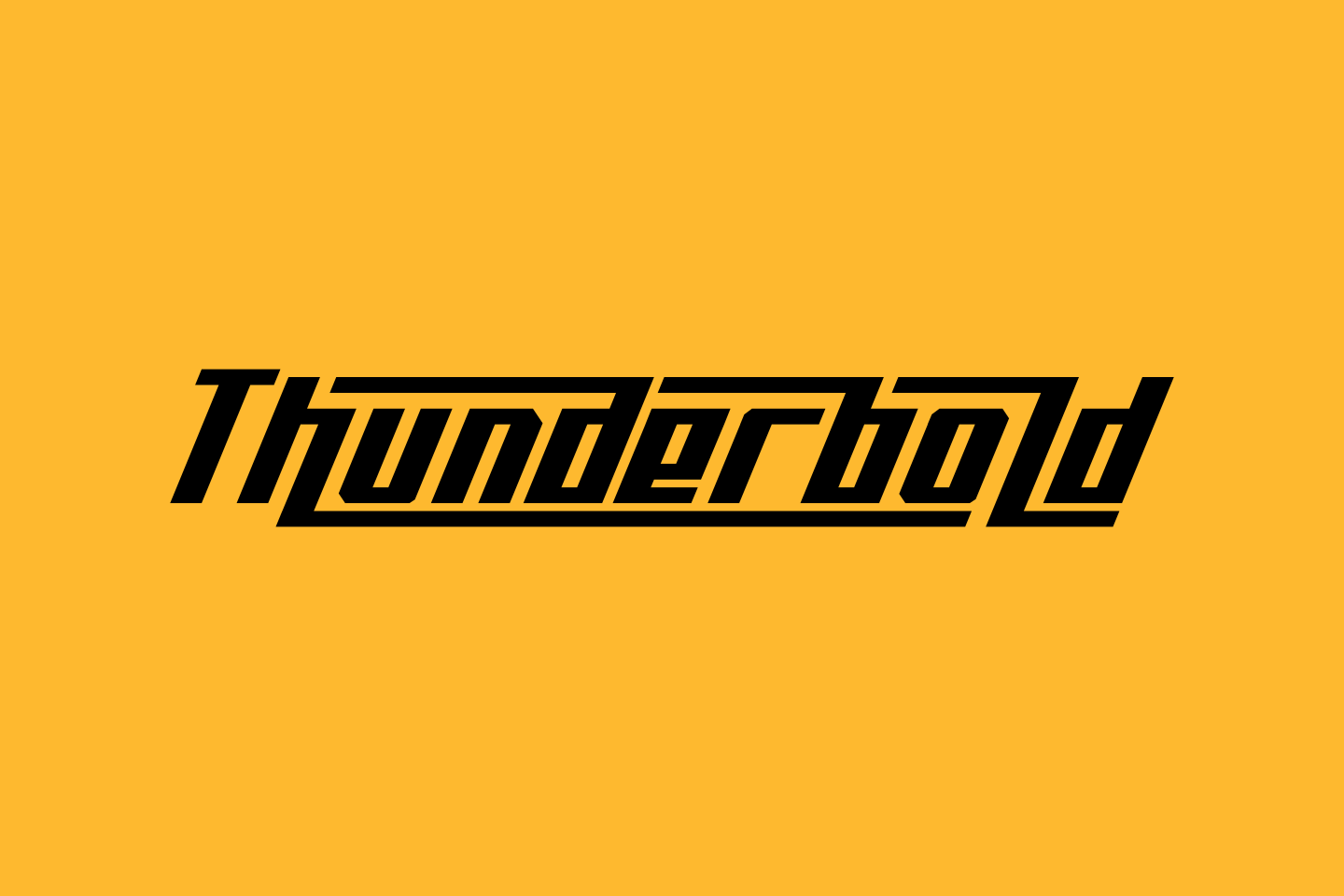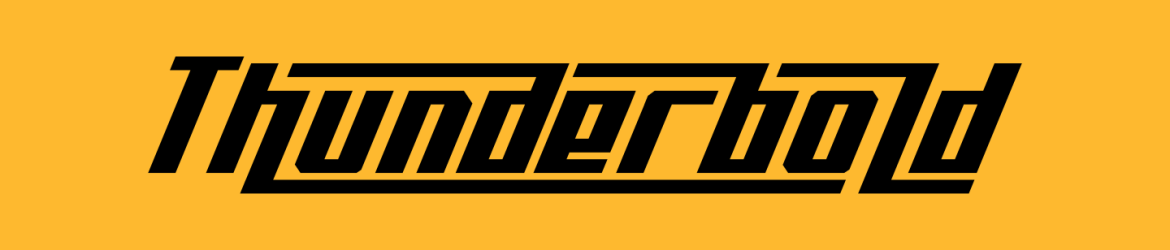
Thunderbold Typeface – Download Grátis
A Thunderbold Typeface é uma escolha perfeita para os projetos que exigem destaque e força visual. Com seu design robusto, esta fonte foi criada especialmente para a mídia outdoor: desde outdoors gigantes até as mais pequenas notificações de corrida. Seu formato bold torna-a ideal para qualquer aplicação onde você deseja chamar atenção à primeira vista. O destaque se deve em grande parte ao seu recurso alternativo, que permite uma variedade infinita de aplicações e criação de novas identidades visuais sem necessariamente ter de recorrer a fontes adicionais. Seu design poderoso faz-a perfeitamente adequada para logotipos e marcas de negócios, bem como banners, outdoors, selos de corrida ou quaisquer outros casos que exigem um apelo impactante. Composta para destaque em grandes escala, a Thunderbold é uma escolha segura se você está procurando uma fonte que dará o tom a qualquer projeto onde deseja impressionar seus espectadores. Se você estiver buscando uma fonte poderosa e versátil para suas criações de design gráfico, não perca tempo: a Thunderbold Typeface certamente atende às suas necessidades.